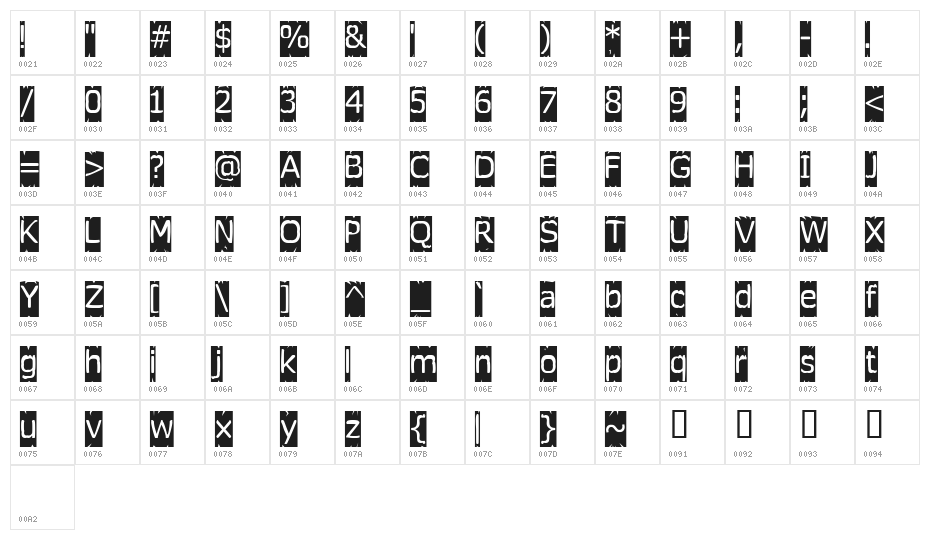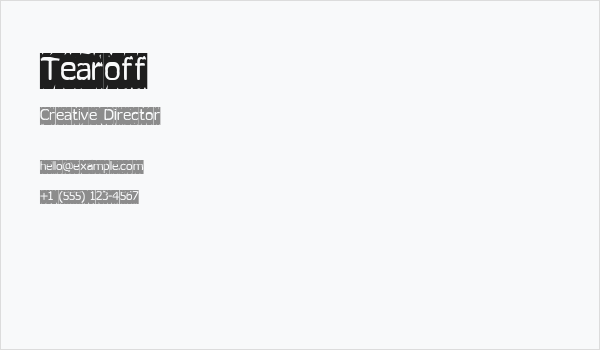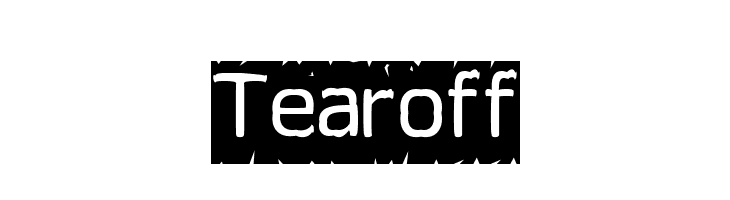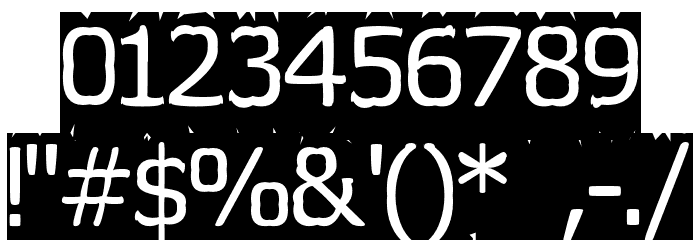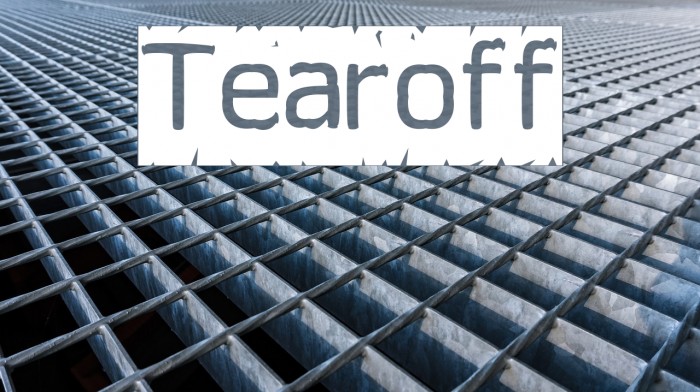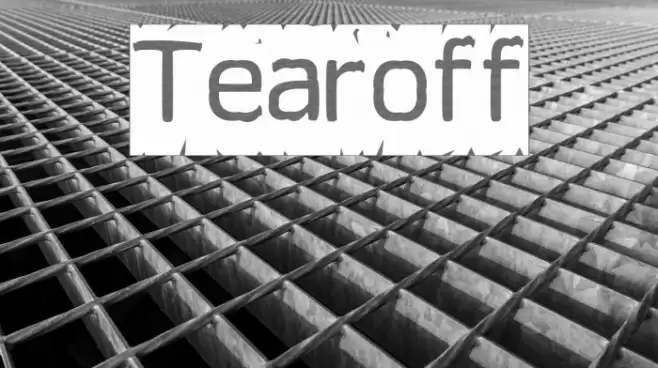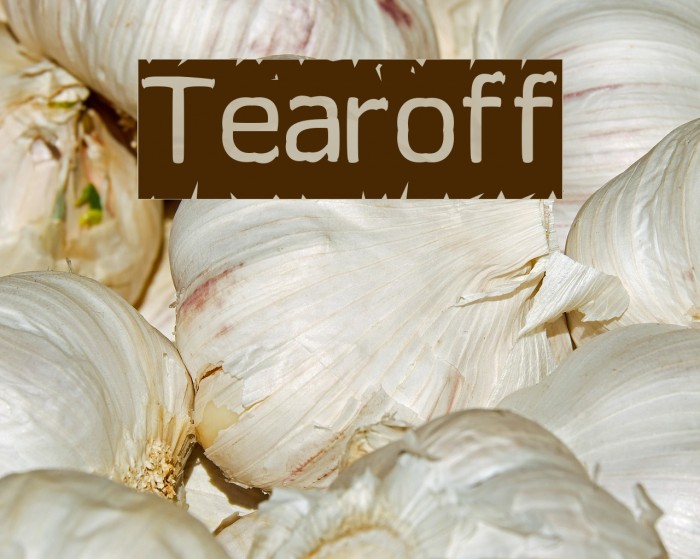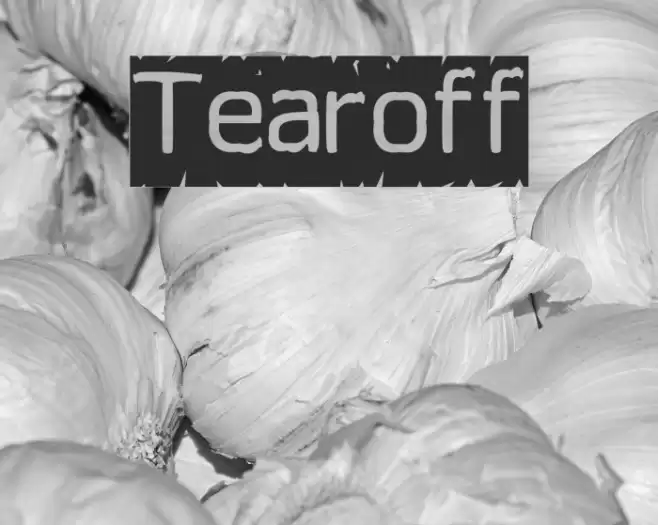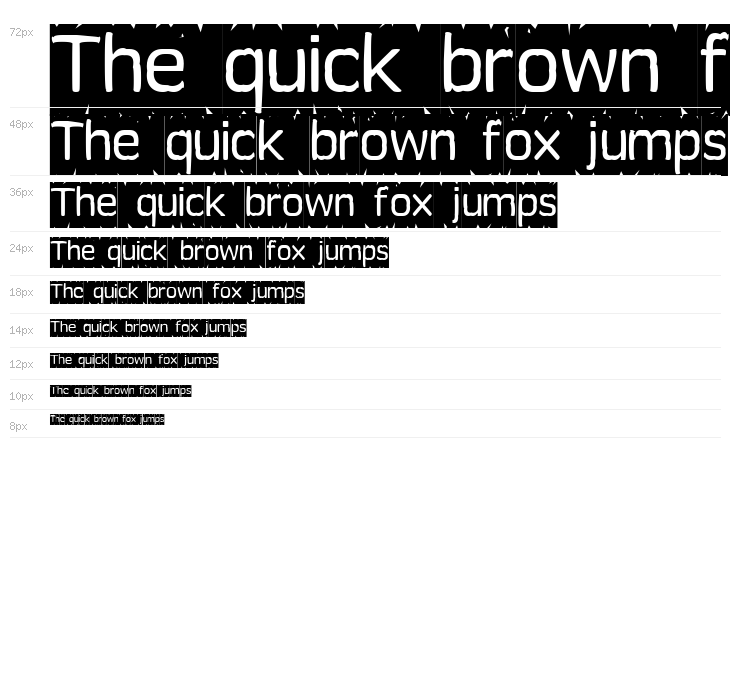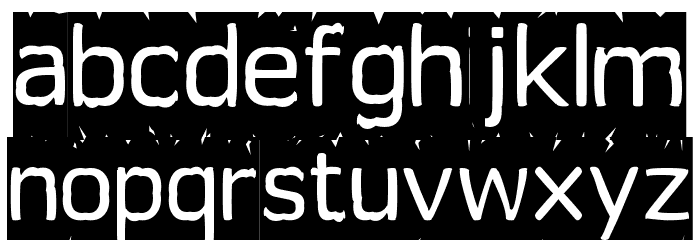
Tearoff Font
Fonts by Graham Meade - GemFonts
| Estilo geral | Modern, Decorative |
| Projetos propostos | Ideal for posters, album covers, branding, and any design needing a bold, artistic touch. |